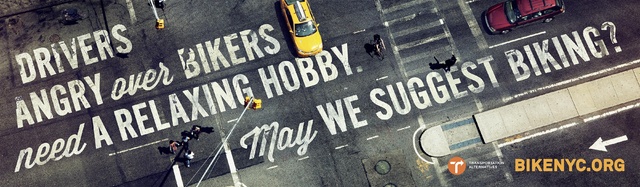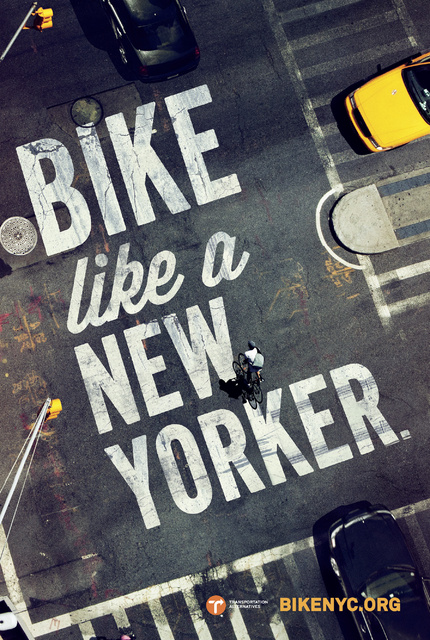
Schreibschrift und Serifenlose
Ja, die Serifenlose könnte hinhauen.
Das größere Problem is die "50ger Retro" - Schrift.
Ich habe Ähnliche gefunden, die sind aber alle unten bei den Verbindungen nicht so geschwungen, sondern eher eckig...
Auch von der Strichstärke ist diese recht eigen...
Die League Gothic wäre übrigens noch eine der kostenlosen Kandidaten.
Diese Retro-Script kommt mir auch nicht sooo unbekannt vor … welche waren denn die Ähnlichen?
Tatsächlich; die League Gothic kommt dem am ehesten nahe. Viell. ist es gar die selbe Schrift? ( vor allem wenn ich mir das "S" und das "G" anschaue kommt es mir identisch vor )
Hab mir den Artikel mit Romney durchgelesen, die Schrift die er auf den T-Shirts verwendte kommt mir dünner vor? Wenn es tatsächlich diesele Schrift ist, hat der angeheurte "Grafiker" seine Hausaufgaben nicht gemacht... ( aber da hab' ich grade nicht wirklich zu reden, was? ;-)
Aber ich glaube das ist sie. Kann man die irgendwo umsonst kriegen? Bzw. eine ähnliche nachgebaute? Habe ein paar seiten gefunden, wo steht das es ein "free font" ist, wobei ich dann aber imer auf die Seite vom "LOSt TYPE" zu James T. Edmondson weitergeleitet werde und dort steht kein freier Download zur verfügung?
Hab mir den Artikel mit Romney durchgelesen, die Schrift die er auf den T-Shirts verwendte kommt mir dünner vor
Wenn man genau hinschaut, sieht man, dass da eine weiße Kontur drum- bzw. drübergelegt wurde… :oops: naja.